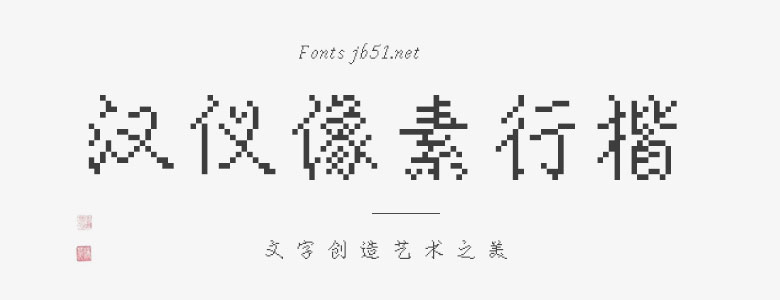
漢儀像素行楷15pxj將傳統(tǒng)的行楷書法與現(xiàn)代的像素藝術(shù)相結(jié)合,創(chuàng)造出一種新穎且獨(dú)特的視覺效果。這種風(fēng)格既保留了行楷的流暢與優(yōu)雅,又增添了像素化的趣味與創(chuàng)意,適合應(yīng)用于藝術(shù)設(shè)計(jì)、平面宣傳設(shè)計(jì)、網(wǎng)頁設(shè)計(jì),書法字帖等領(lǐng)域。